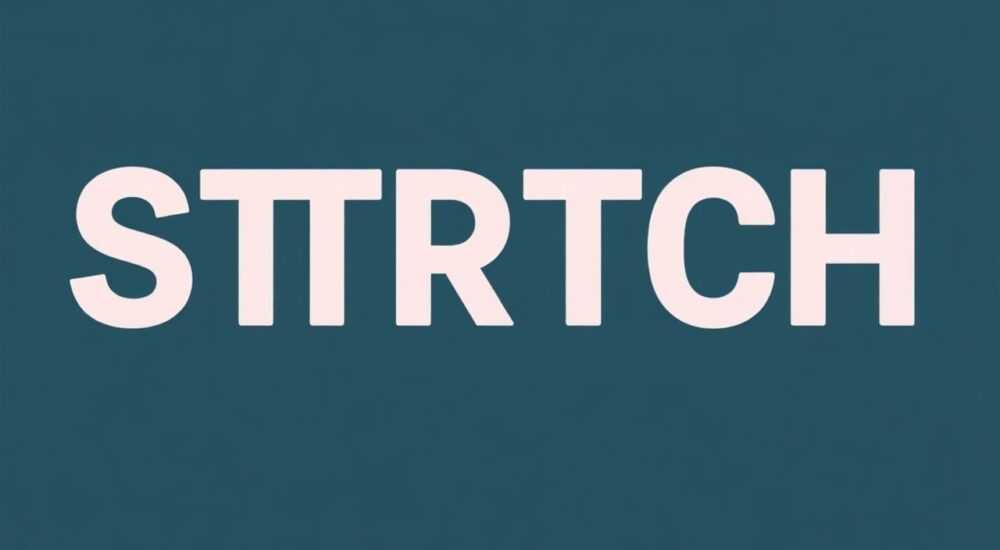
Как растянуть шрифт в высоту в фигме
Когда вы работаете в Figma и сталкиваетесь с необходимостью визуально растянуть шрифт по высоте — например, чтобы текст в заголовке идеально вписался в контейнер, создал нужный визуальный акцент или соответствовал макету дизайн-системы — вы не просто меняете размер шрифта. Вы работаете с пропорциями, гармонией и восприятием. Но Figma не предоставляет прямого инструмента для растяжения шрифта по вертикали, как это делают графические редакторы вроде Adobe Illustrator. Это не ошибка, а особенность. И понимание этой особенности — ключ к решению задачи без потери качества.
Почему нельзя напрямую растянуть шрифт в Figma
Figma — это инструмент для дизайна интерфейсов, а не векторной графики. Его типографическая система основана на стандартах веба и мобильных платформ, где шрифты должны оставаться масштабируемыми, но не искажёнными. В отличие от Illustrator или Photoshop, где можно свободно менять ширину и высоту текста через «Free Transform», в Figma текст остаётся «живым» — то есть сохраняет свою типографическую структуру. Любое изменение высоты через растяжение нарушает метрики шрифта: высоту заглавных букв, расстояние между базовой линией и верхней границей, а также пропорции серифов и засечек.
Представьте, что вы растягиваете шрифт Helvetica в 2 раза по высоте. Буква «O» превратится в овал, буква «H» — в узкую колонну, а засечки на «T» — в тонкие линии, почти не различимые на экране. Это не просто «выглядит плохо» — это нарушает принципы типографики, которые были разработаны веками.
Это ограничение — не недостаток, а фича. Оно защищает вас от типографических ошибок, которые легко допустить в спешке. Но если вам действительно нужно визуально растянуть текст — есть несколько надёжных способов, которые не разрушат ваш макет.
Метод 1: Использование свойства Scale
Самый простой и быстрый способ — использовать свойство «Scale» в панели свойств (Properties). Он не изменяет размер шрифта, но масштабирует весь слой, включая текст, как векторный объект.
1. Выделите текстовый слой.
2. В правой панели найдите раздел «Scale».
3. Установите значение по вертикали (Y) выше 100% — например, 120% или 150%.
4. Оставьте горизонтальное масштабирование (X) на 100%, чтобы не искажать ширину символов.
Этот метод сохраняет чёткость текста, потому что Figma масштабирует текст как вектор, а не растрирует его. Он идеально подходит для временных макетов, прототипов или когда вы работаете с системой, где текст должен «вписаться» в фрейм, но не требует идеальной типографики.
Однако есть нюанс: если вы используете этот метод в компонентах, масштабирование может наследоваться некорректно. Также, если вы экспортируете текст в PNG или SVG, масштабированный текст может выглядеть немного размытым на низких DPI.
Метод 2: Преобразование в контуры
Если вам нужен полный контроль — преобразуйте текст в контуры. Это превращает каждый символ в набор векторных точек, которые можно свободно перемещать, растягивать и искажать.
1. Выделите текстовый слой.
2. Нажмите Ctrl/Cmd + Shift + O или выберите в меню: Object > Convert to Vector.
3. После преобразования текст станет набором векторных форм — вы больше не сможете редактировать текст как символы.
4. Используйте ручку (Select Tool) и тягайте за угловые точки, чтобы растянуть текст по вертикали.
Этот метод даёт максимальную гибкость. Вы можете сделать буквы «высокими и узкими» — как в логотипах, или «вытянутыми и театральными» — как в рекламных баннерах. Особенно полезен для создания кастомных шрифтов, логотипов и стилизованных заголовков.
Но будьте осторожны: после преобразования в контуры вы теряете возможность менять текст. Если нужно внести правки — придётся создавать новый слой. Также, если вы работаете в команде, важно предупредить других дизайнеров: «Этот текст уже не редактируется».
Метод 3: Ручная настройка межстрочного интервала и высоты строки
Иногда «растяжение» — это не физическое изменение формы символов, а визуальное ощущение большей высоты. Это достигается за счёт увеличения межстрочного интервала (Line Height) и высоты строки (Height).
1. Выделите текст.
2. В панели Properties найдите параметр «Line Height».
3. Увеличьте его до значения, превышающего размер шрифта — например, при размере 24px установите Line Height = 40px.
4. Для ещё большего эффекта — увеличьте высоту фрейма, в котором находится текст.
Такой подход не меняет форму букв, но создаёт ощущение «воздушности» и «высоты». Особенно эффективен для заголовков в современных интерфейсах — например, в дизайне приложений типа Notion, Apple Music или Figma-самого.
Этот метод идеален, если вы работаете с системой дизайна, где важно сохранить доступность и читаемость. Он не требует преобразования в контуры и не нарушает типографику.
Метод 4: Работа с фреймами и Auto Layout
Если вы хотите, чтобы текст автоматически подстраивался под высоту контейнера — используйте Auto Layout.
1. Оберните текстовый слой в фрейм.
2. Включите Auto Layout (кнопка в панели свойств).
3. Установите направление — Vertical.
4. Выберите «Fill container» для высоты.